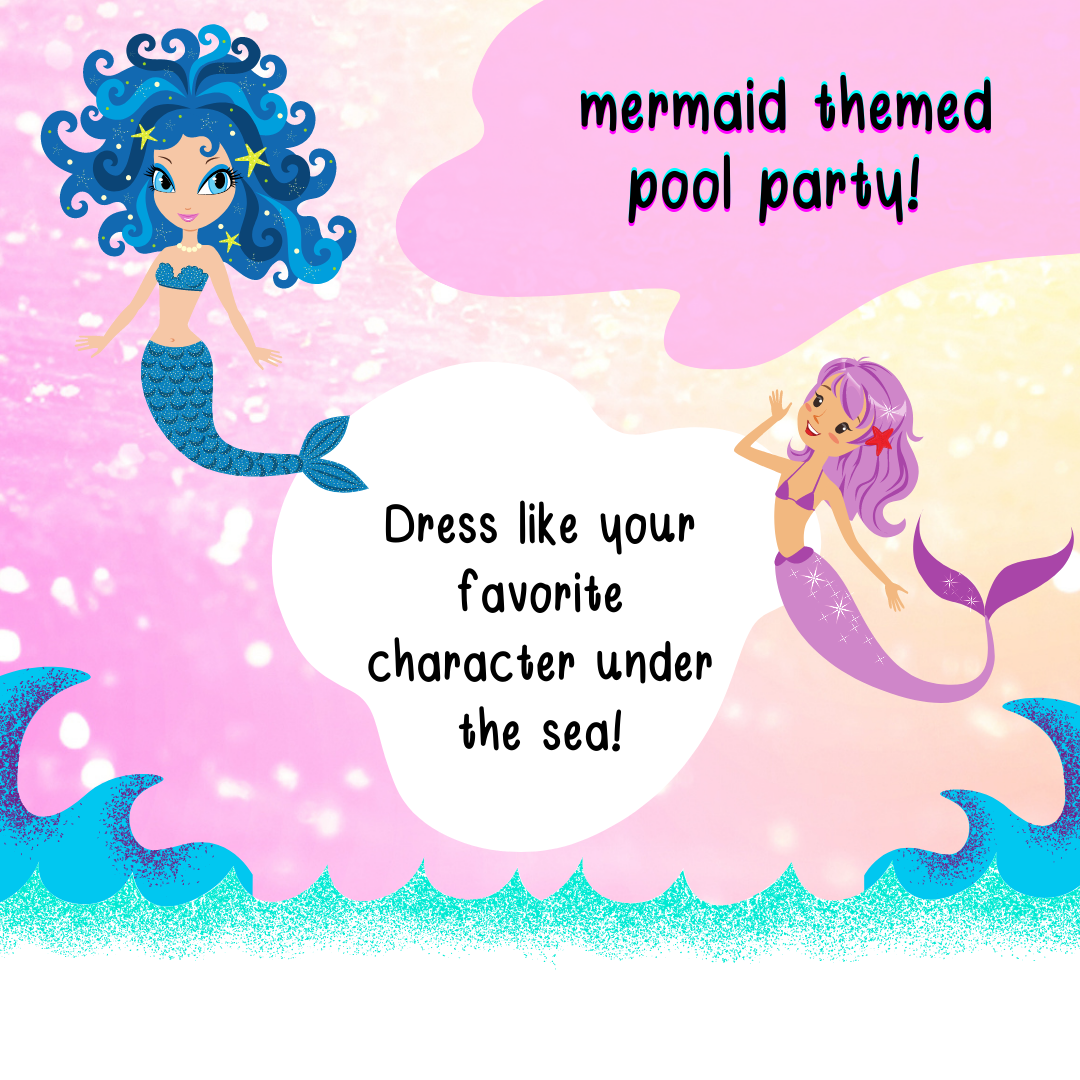
ฟอนต์ อีธาน (Ethan)
ฟอนต์  อีธาน(Ethan) ฟอนต์ที่มีเอกลักษณ์ ใช้ทำงานสไตล์น่ารักๆ จดโน้ต หรือจะทำแฟลชการ์ดก็ดูดี แจกฟรีไปเลยเวอร์ชันทดลอง : แบบปกติ 1 น้ำหนัก ใช้ได้เฉพาะแบบส่วนตัว เช่น ใช้ในการศึกษา ใช้จด ใช้ตกแต่งสมุดโน้ตตัวเอง